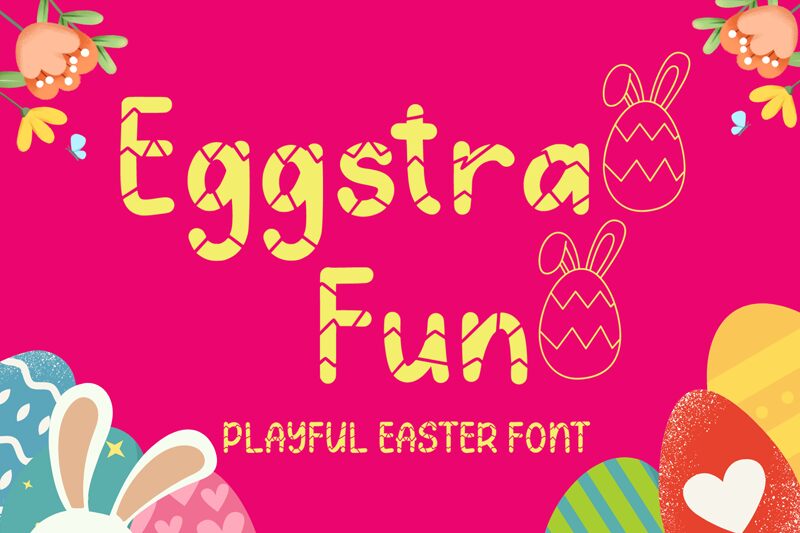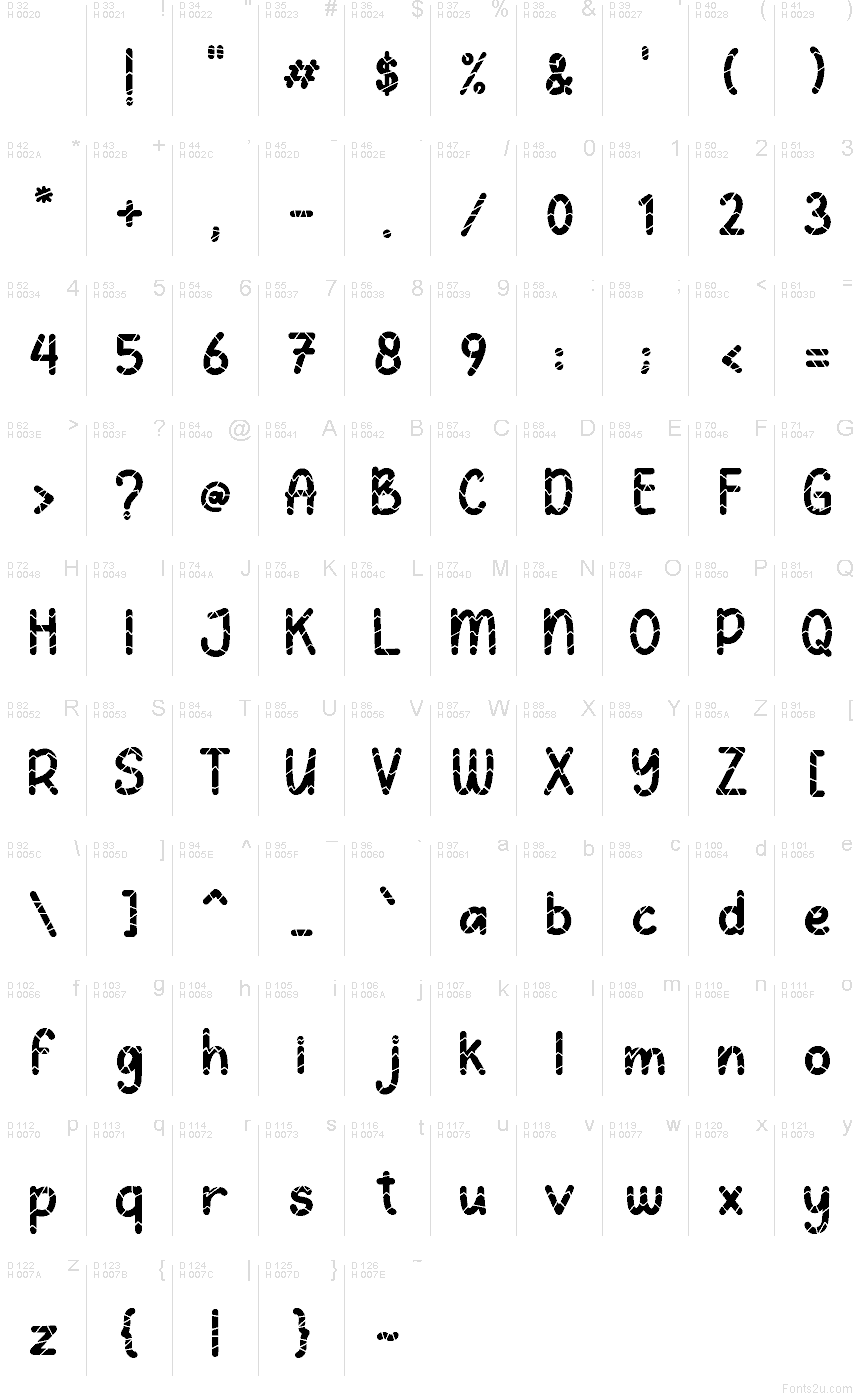
Eggstra Fun
AEN Creative Studio 推出的 Eggstra Fun 是一款免费展示字体,其字形基于破碎的蛋壳设计。连续的裂纹与圆润的边缘赋予了字母“破壳而出”的质感,完美契合春日主题,让你的设计不再局限于平凡的装饰。
这种蛋壳纹理非常适合用于复活节贺卡、寻蛋游戏传单、烘焙包装、季节性社交媒体帖子以及课堂讲义的短标题。它同样适用于工艺品标签和邀请函,破碎的造型能与彩蛋、糖果包装纸等节日元素巧妙呼应,无需额外插图即可营造出浓厚的节日氛围。